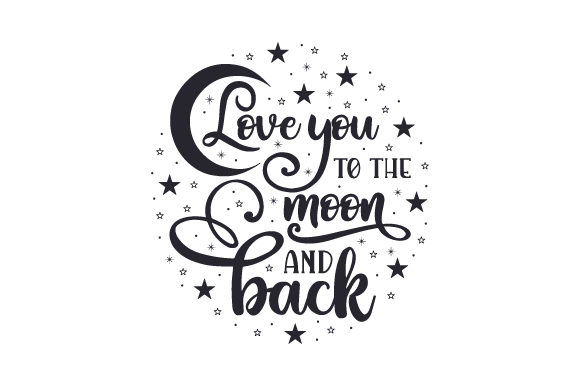
Love You to the Moon and Back
Trouver les bons éléments de conception peut être un défi, mais Love You to the Moon and Back propose une collection exceptionnelle qui rehausse instantanément votre travail.
Conçu avec précision, Love You to the Moon and Back offre des vecteurs nets, une typographie fluide et une licence commerciale pour une tranquillité d'esprit.
Que vous créiez des produits POD (impression à la demande), des invitations de mariage ou des visuels pour les réseaux sociaux, Love You to the Moon and Back est un choix idéal.